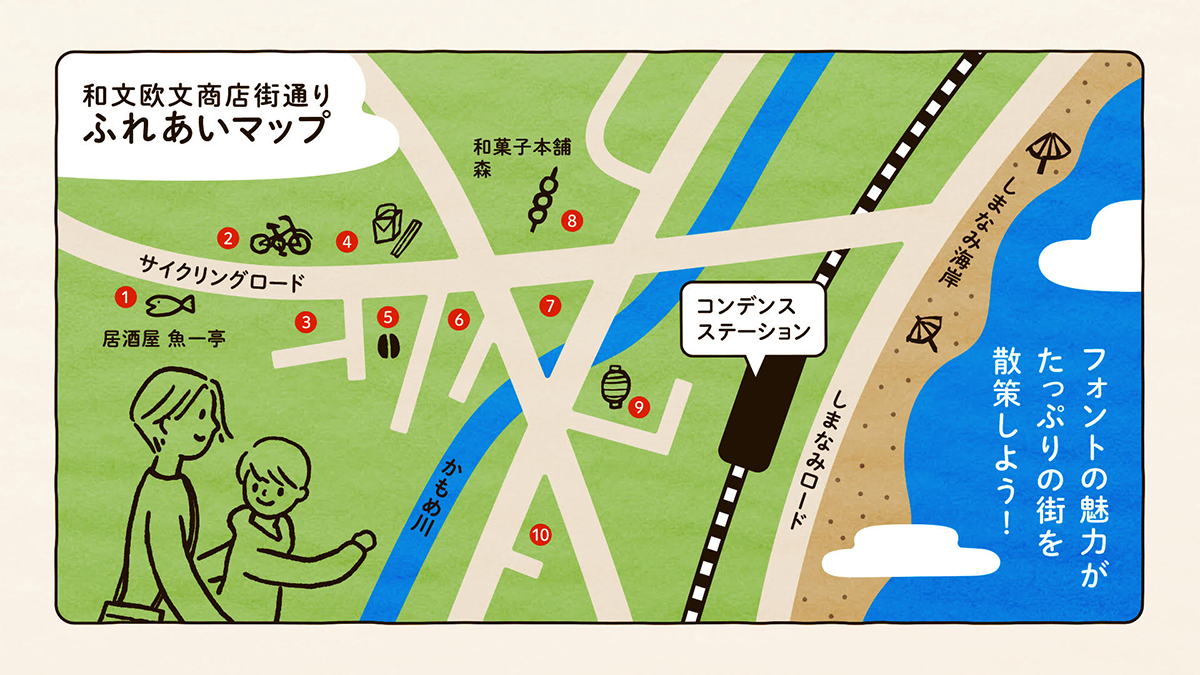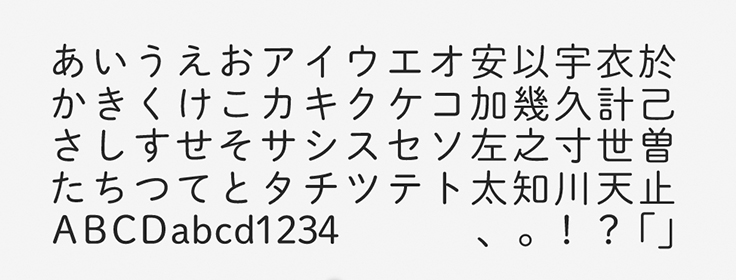
「秀英丸ゴシック」について
秀英体ファミリーの1つで、モリサワでは秀英明朝と合わせやすいL・Bの2ウエイトを展開しています。秀英体は大日本印刷が前身である秀英舎の時代から100年以上にわたって開発を続けている伝統ある書体です。秀英丸ゴシックは、その秀英体の利用範囲を広げるために開発したもので、クラシックな印象の丸ゴシック体となっています。
「秀英丸ゴシック」の特徴
小ぶりな字面であることが特徴で、一般的な字面が大きい丸ゴシック体とはやや異なる趣を出すことができます。字面が大きいとそれぞれの文字に大らかさがある一方で組んだときの圧迫感もありますが、字面が小さい秀英丸ゴシックには窮屈な印象はありません。
ふところを締めた丸すぎない設計で、さりげなくほのぼのとした印象を与えます。丸ゴシック体というと子ども向けの印象も強いですが、本フォントは幼すぎない落ち着いた印象の丸ゴシック体と言えるでしょう。
制作デザイナーの解説コメント
作例は商店街の通りを紹介するマップなので、ほのぼのとした親しみを感じてもらうように秀英丸ゴシックを活用しました。イラストも組み合わせながら、優しい雰囲気を表現すると同時に、どこか落ち着きもあるようなデザインに仕上げています。
書籍、雑誌、チラシ、パンフレット、地図、看板、サイン